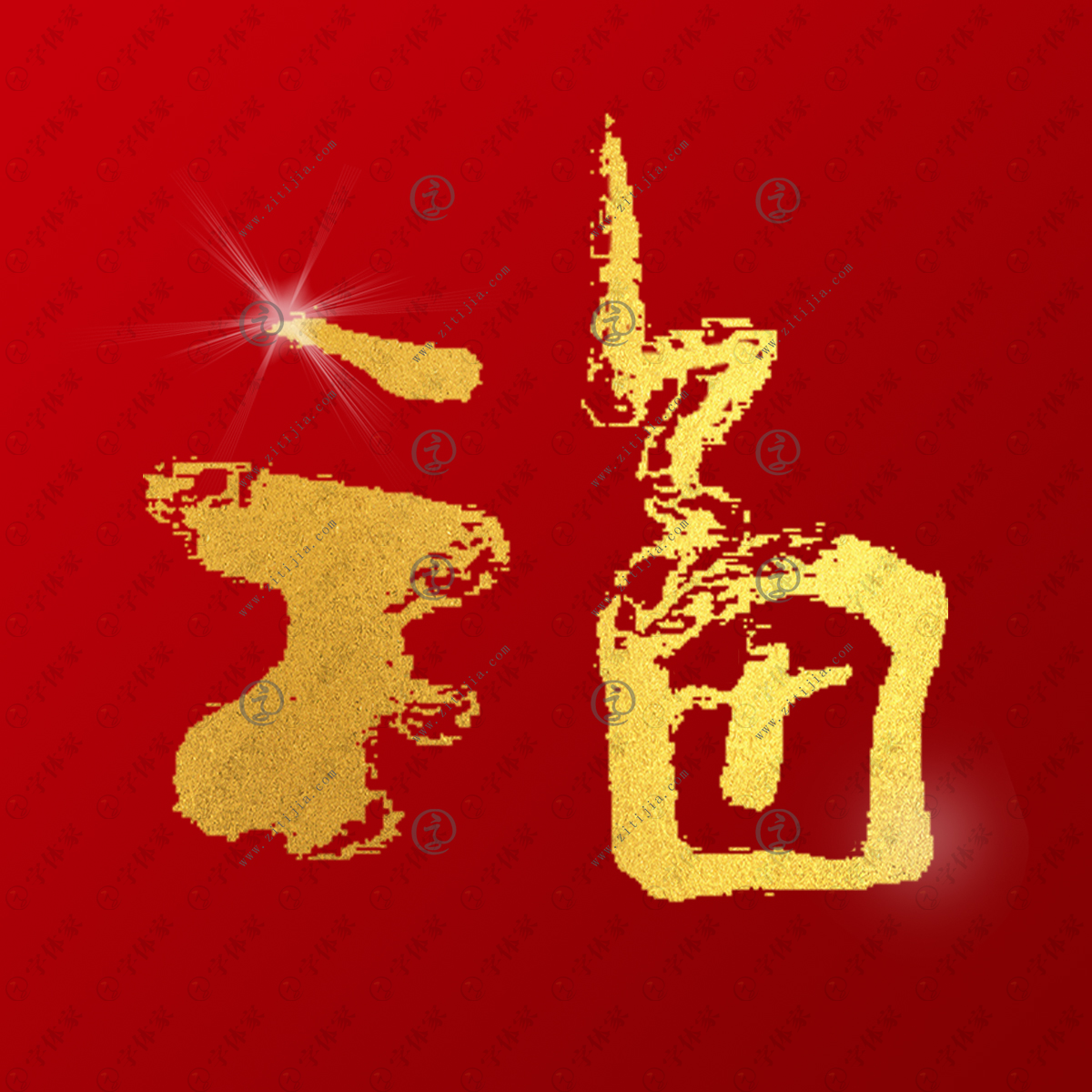
福,会意兼形声字。从河南殷圩出土的甲骨文来看,“福”是双手虔诚地捧着酒坛(酉)敬神(示)的形象,是用“手”、“酒”、“示”三个部分组合成的会意字,原是以酒敬神,祈求福备(万事顺遂)的意思。从上列甲骨文字形来看,它的左半部的上面是个“酉”字,是个盛酒的容器,实际上就是个“酒”字的初文。左下半部分是两只“手”(又),表示双手捧着一个酒樽;它的右半部分是个“示”字,代表祖先的神主;整个字的意思是会意双手捧着一樽酒在祖先的神主前祭献,求得神主保佑。《说文解字》在解释“福”字的意义时说“祐也”,“祐”就是赐福、保佑的意思。